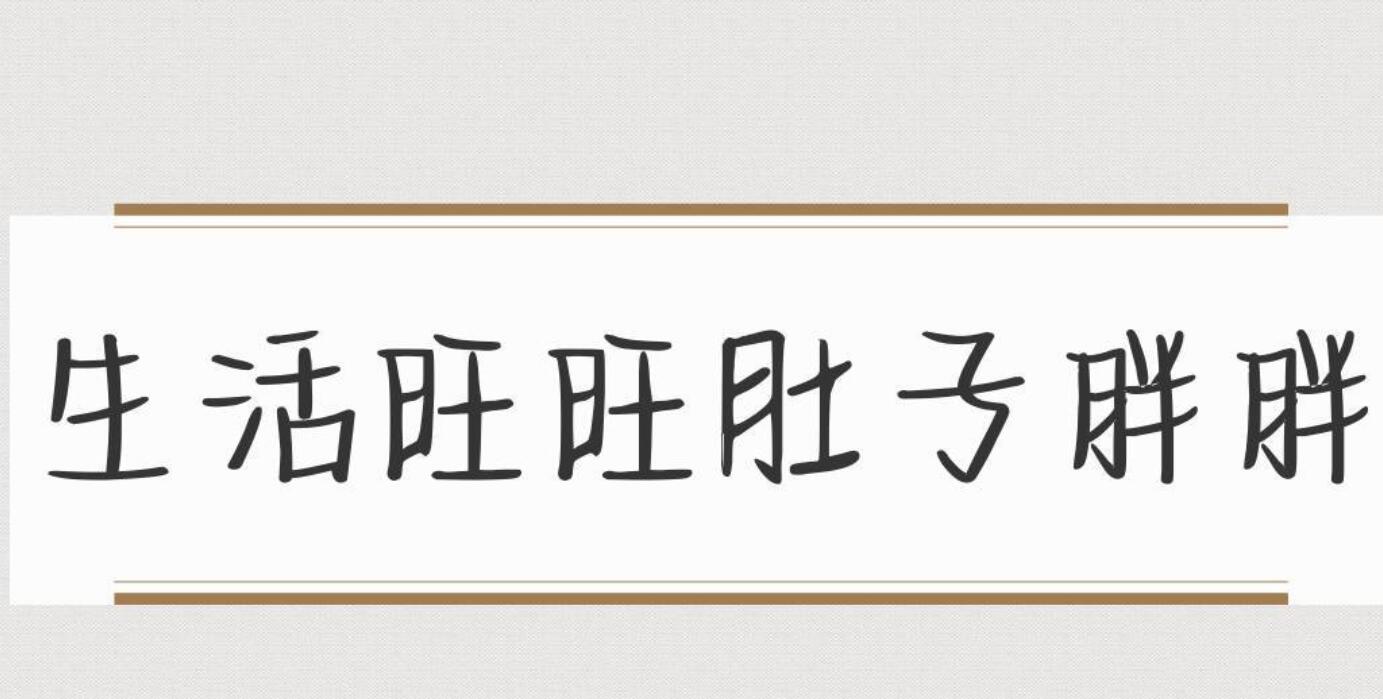
生活旺旺肚子胖胖是文道字庫推出的一款非常不錯的藝術(shù)字體,連貫字跡顯得干練而不凌亂,清新簡明,具有很好的視覺感,適合應(yīng)用于藝術(shù)設(shè)計、平面宣傳設(shè)計、網(wǎng)頁設(shè)計,書法字帖等領(lǐng)域,歡迎喜歡冬日限定草莓字體的朋友前來下載使用。